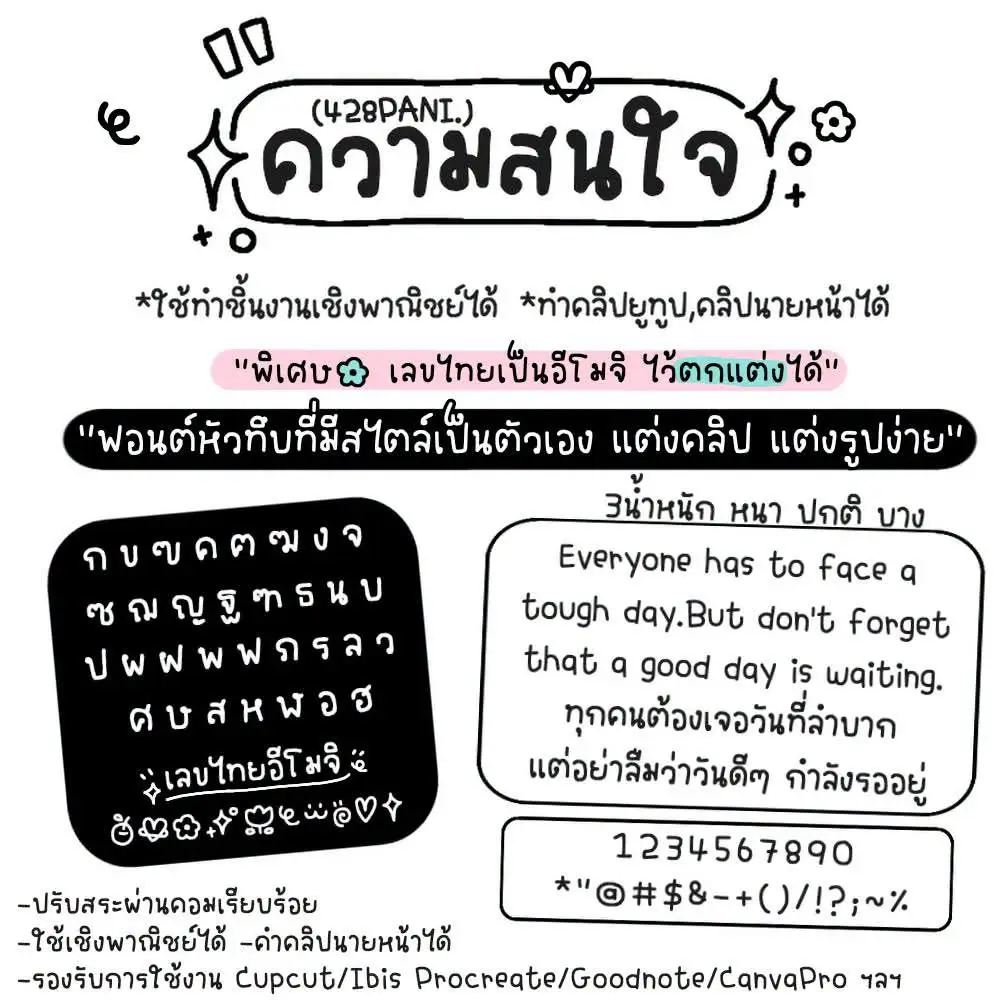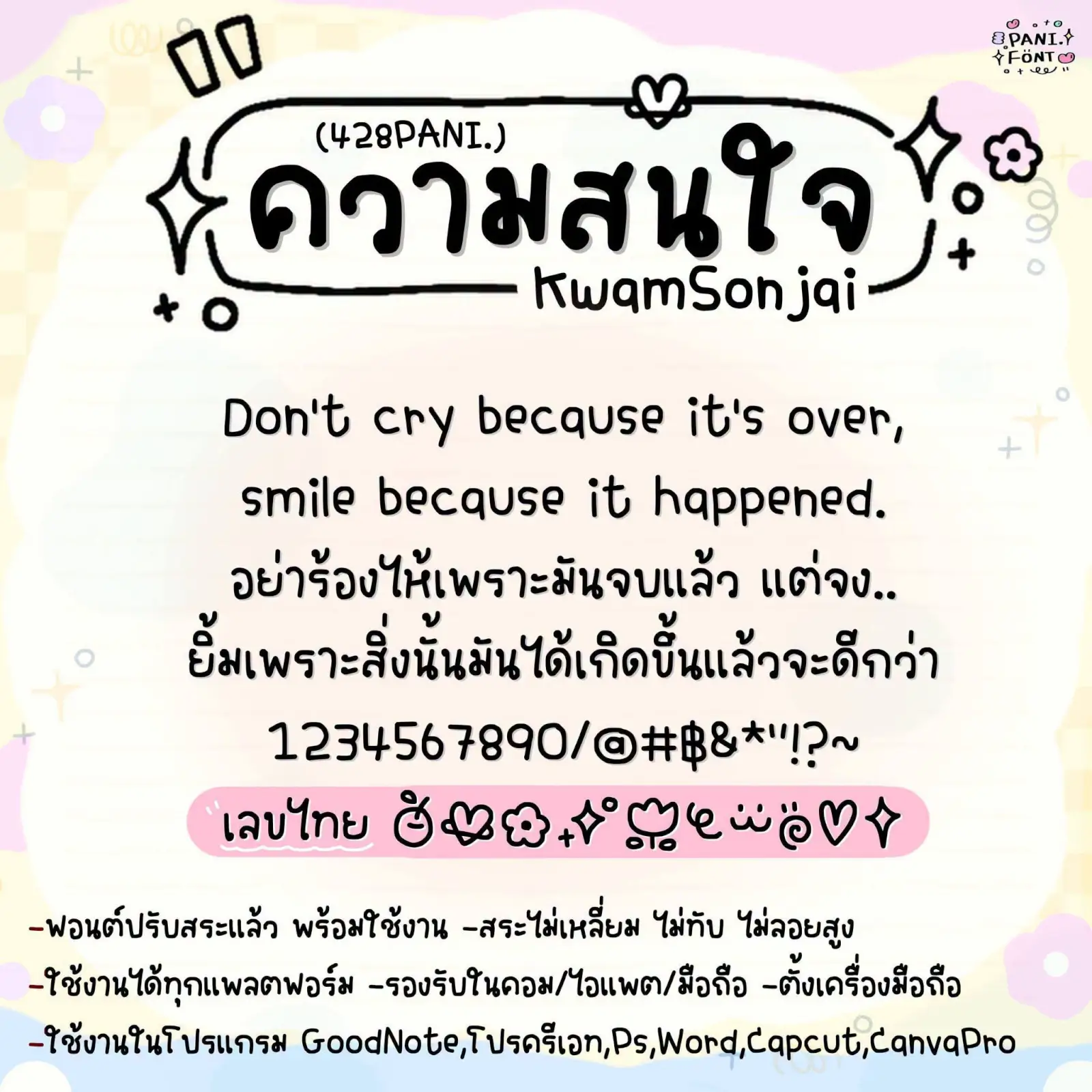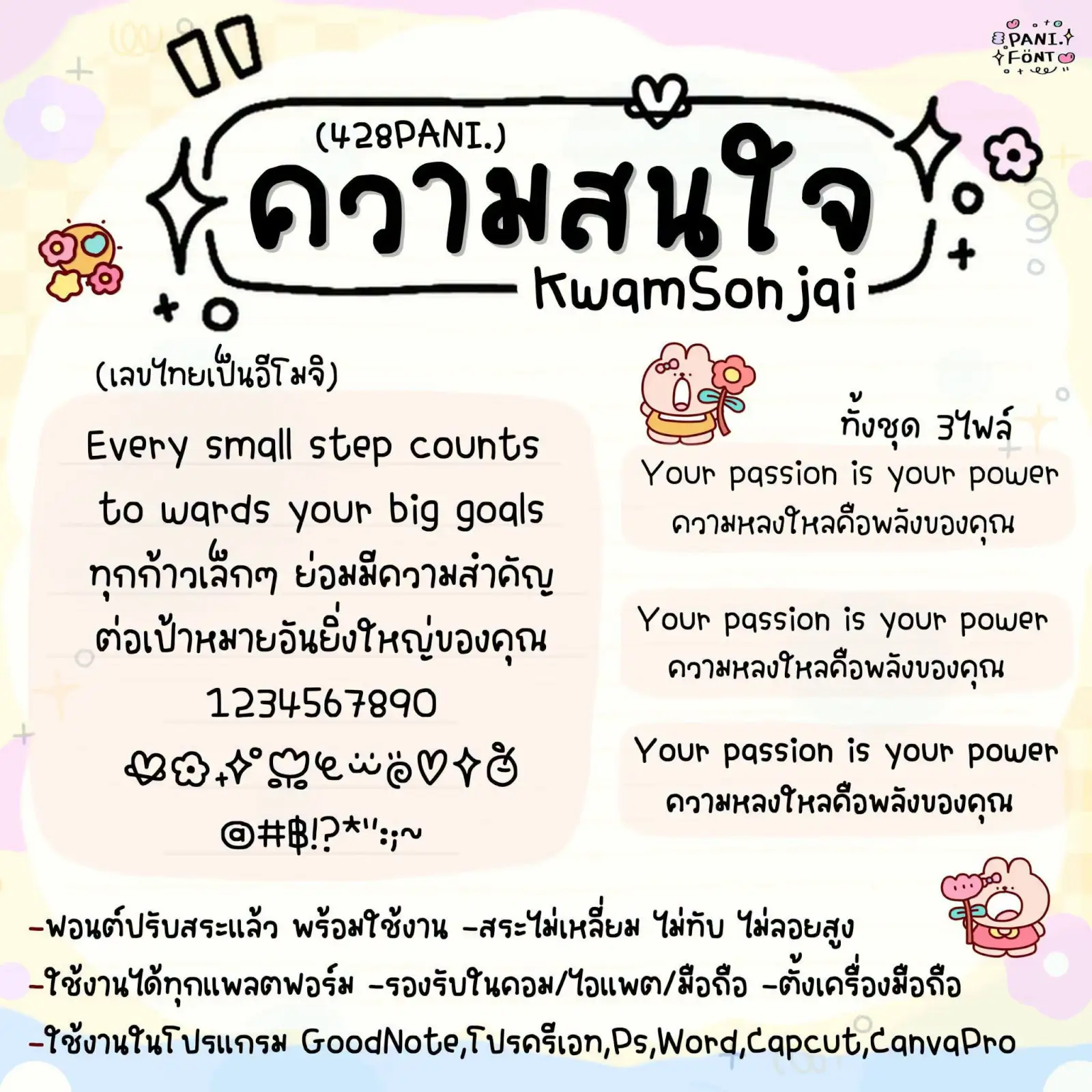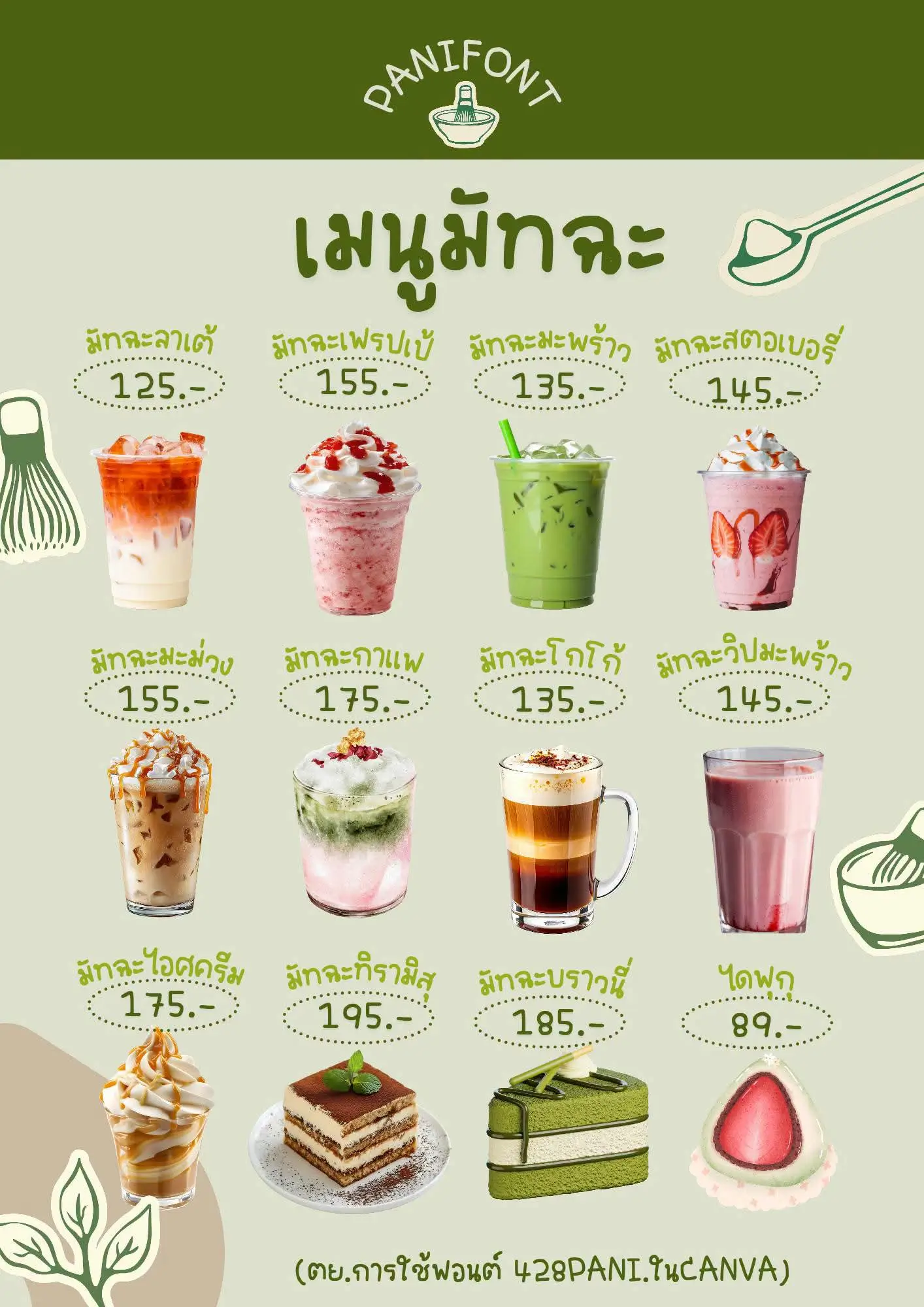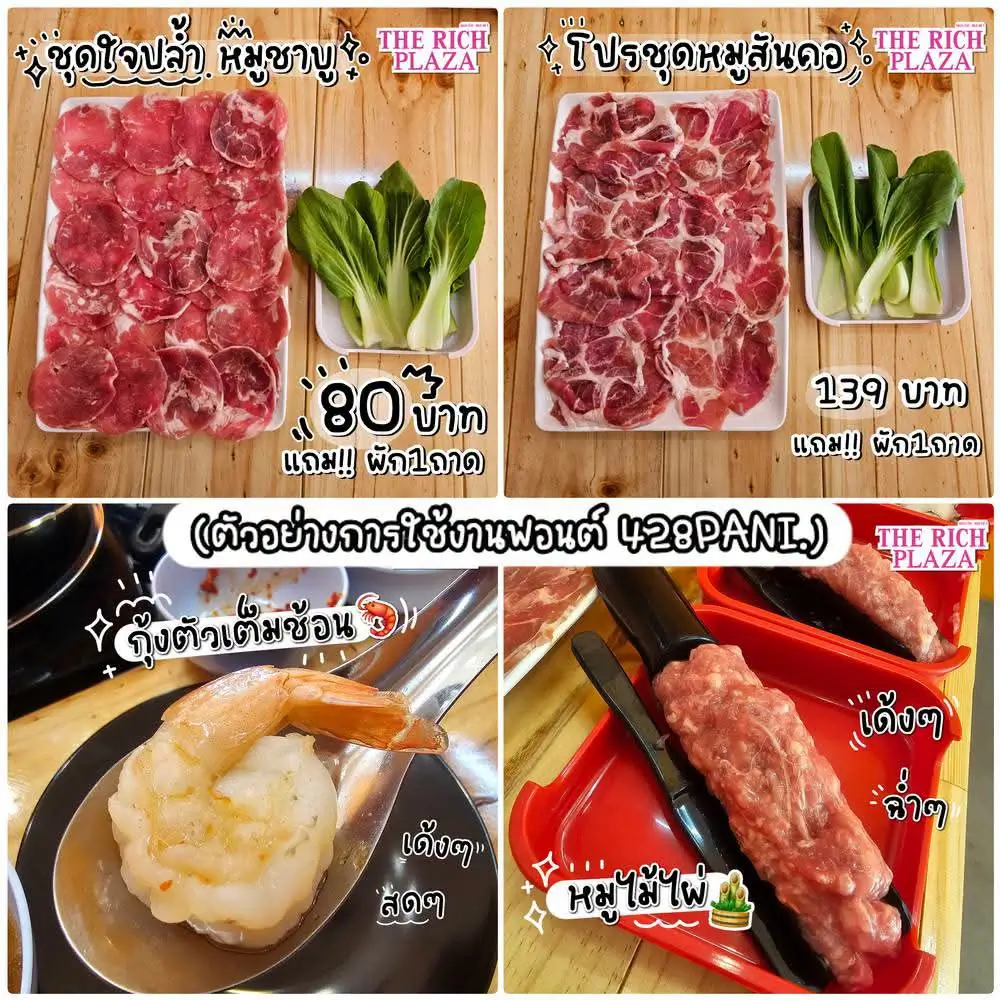
ความสนใจ (428PANIKwamSonjai)
ฟอนต์ 428PANI.ความสนใจ – ฟอนต์ใหม่ค่ะ ใช้คำว่าน่ารักได้เปลืองมากๆ ฟอนต์น่ารัก ฟีลเด็กซนๆ ทันสมัย ใช้งานได้หลากหลาย
จะเป็นฟีลชิดๆ ก็เก๋ จะห่างๆ ก็สบายตา
(อีโมจิเลขไทยไว้ ตกแต่งแนวมินิมyลด้วยค่ะ)